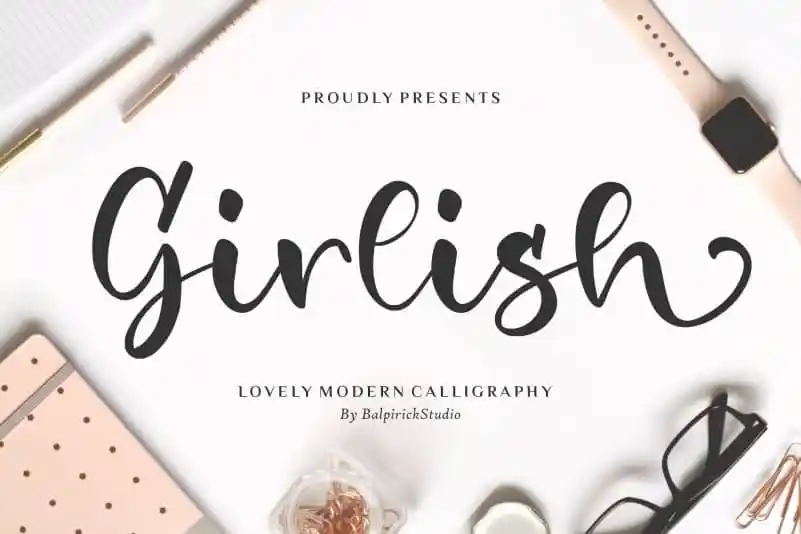
Girlish Lovely Calligraphy Font
A fonte ‘Girlish Lovely Calligraphy Font’ é perfeita para agradáveis aplicativos digitais e projetos visuais do dia-a-dia. Com seu estilo girasol de letras elegantes, essa fonte é ideal para o design de embalagens, criação de marca, revistas, mídias sociais, bem como para destacar frases em um background mais simples no contexto da celebração ou aniversário. Perfeita para quem valoriza a simplicidade e os detalhes, essa fonte oferece uma abordagem elegante que se adequa perfeitamente ao mercado de moda, beleza, cultura digital, entre outros. Seja em um design para aplicativos de social media, logotipos criados ou até mesmo para anúncios, a ‘Girlish Lovely Calligraphy Font’ traz o toque delicado e sofisticado que os consumidores desejam. Não importa o contexto, a letra do estilo girasol apresenta um charme que faz com que seu design se destaque. Esta fonte é uma escolha inteligente para designers e criativos que valorizam o cuidado em sua arte digital.